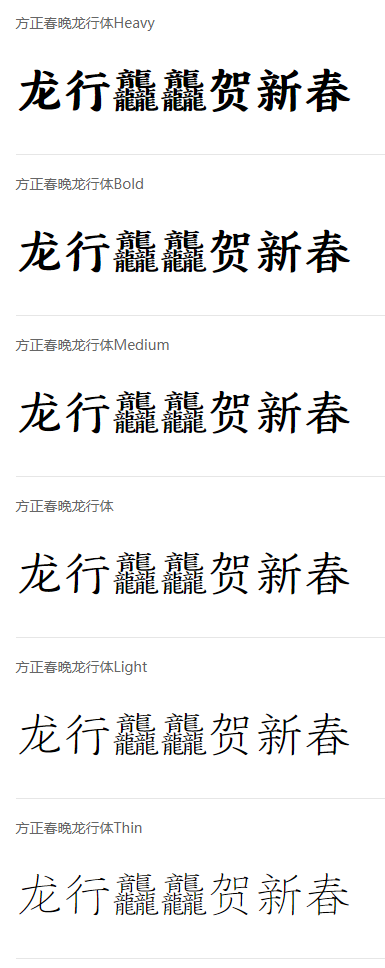
方正春晚龙行体家族
字体品牌: 方正字库 设计师:王贝宁,何诗旸,郭毓海 字体分类:宋体 字体属性:精品字 字符集:大陆简体(GB2312-80) 发布时间: 2024
中央广播电视总台春节联欢晚会是中央广播电视总台在每年除夕之夜为了庆祝新年而开办的综合性文艺晚会。晚会涵盖小品、歌曲、歌舞、杂技、魔术、戏曲、相声等多种艺术形式,把现场观众和电视机前的观众带入到狂欢之中,打造“普天同庆,盛世欢歌”的节日景象。中央广播电视总台《2024年春节联欢晚会》以“龙行龘龘,欣欣家国”为主题,以“龘龘”之姿迈入充满希望的甲辰龙年。
为了庆贺龙年,方正字库为中央广播电视总台春节联欢晚会定制了方正春晚龙行体。此款定制字体灵感来源于被誉为“中华第一龙”的红山文化玉龙,在辽阔的东北大地,红山文化犹如一颗璀璨的明珠,述说着古人的智慧与匠心。
方正春晚龙行体融合了宋体的端庄与楷体的力度,同时,更巧妙地融入了红山文化玉龙的形态与神韵。每一笔、每一划,都仿佛有龙的影子,优雅而威严,古老而现代。每一个字符,都像是一首古老的诗歌,讲述着龙的故事。其文雅之风,体现在字体的每一个细节之中。
在笔画细节的描绘中,我们汲取了宋代刻板样式的精髓,使得笔画更为饱满,字面更趋开阔,从而更适宜于屏幕小字阅读,为广大观众带来了清晰舒适的阅读体验。此外,方正春晚龙行体笔画的特征显著,装饰感十足,其遒劲灵动的风格与龙的形象极为相似。这种字体设计的艺术美感,不仅彰显了传统文化的独特魅力,也赋予了字体更丰富的文化内涵。
方正春晚龙行体,一款承载着红山文化玉龙精髓和中华龙文化的字体,将传统与现代完美融合,展现出文雅而威严的风采。让我们在每一次书写、每一次使用中,都能感受到那份源自古老红山的龙韵,让中华龙文化继续在现代社会中腾飞。
字体主创:中文:王贝宁;西文:何诗旸、郭毓海;设计指导:汪文